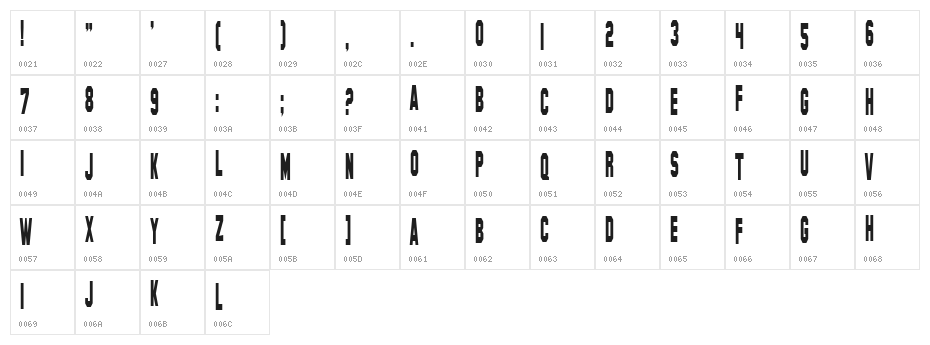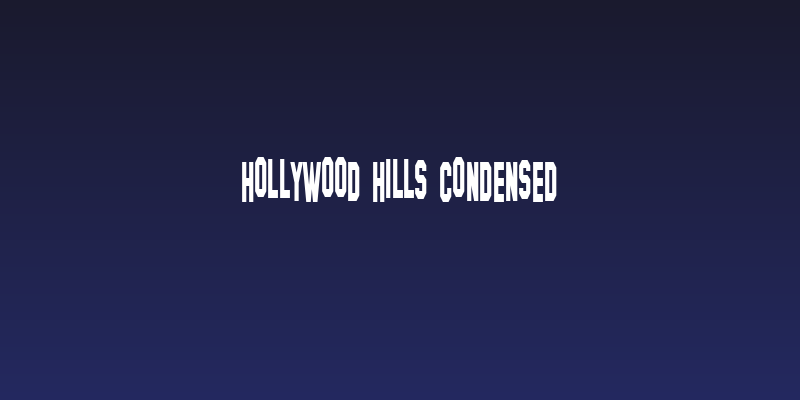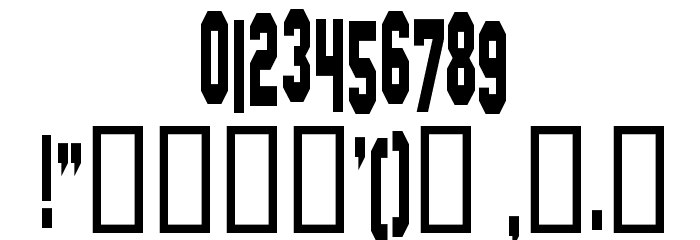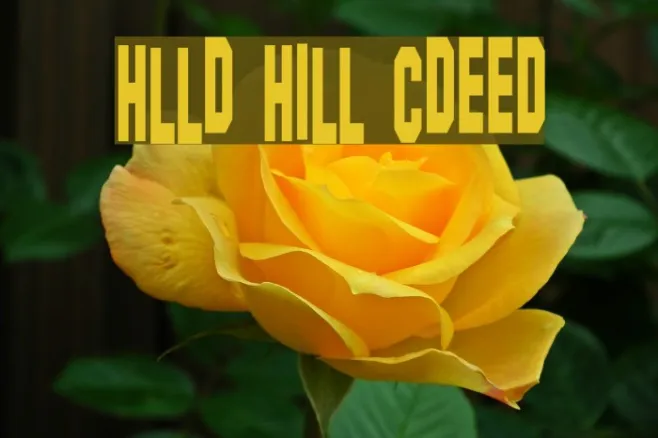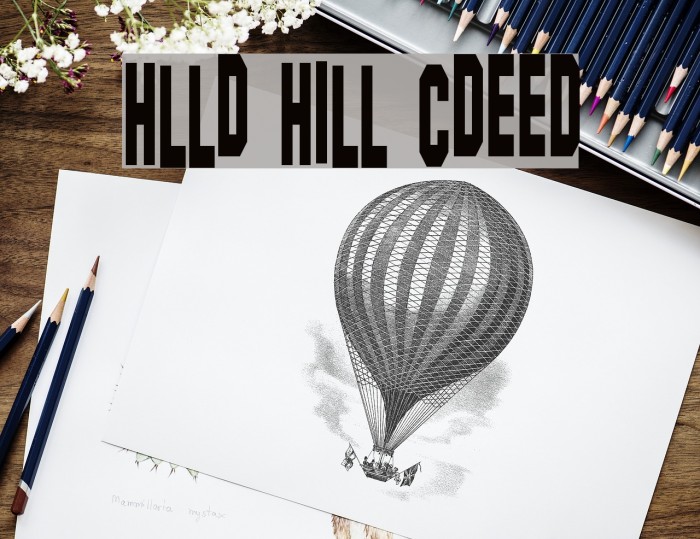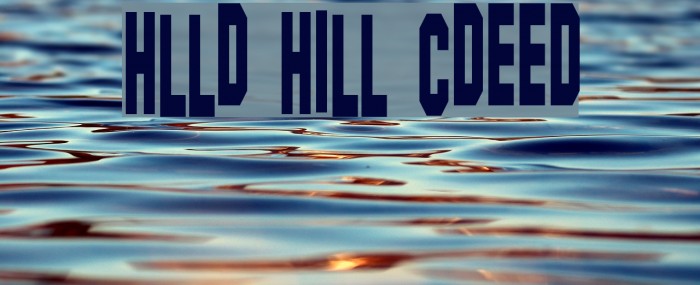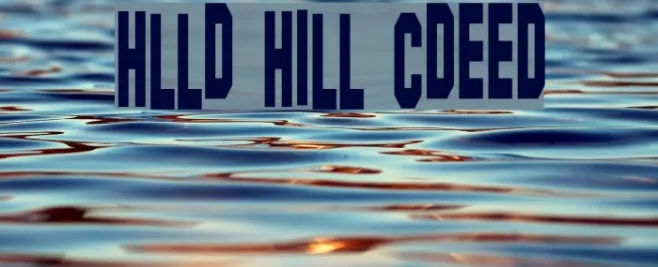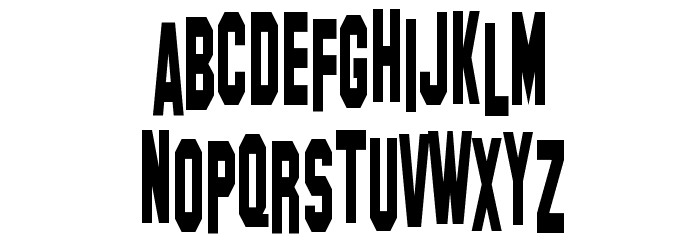
Hollywood Hills Condensed Font
| Vorgeschlagene Projekte | Ideal for movie posters, magazine covers, and branding materials where a strong, impactful presence is needed. |